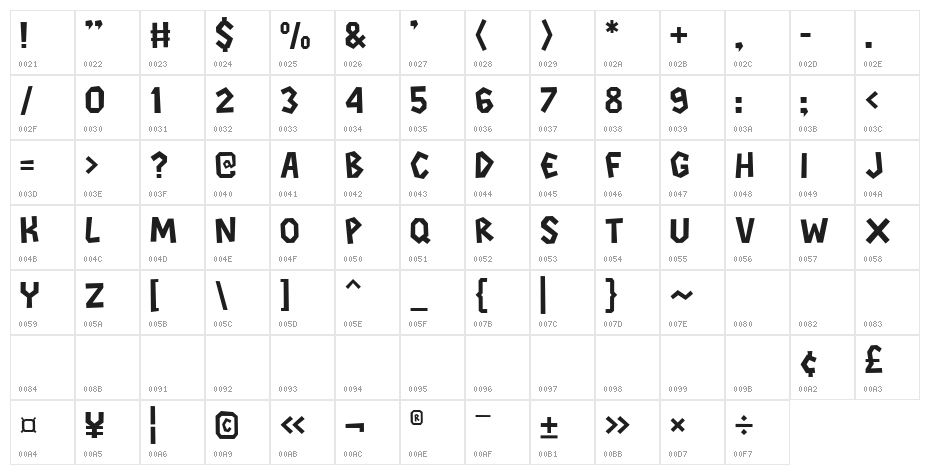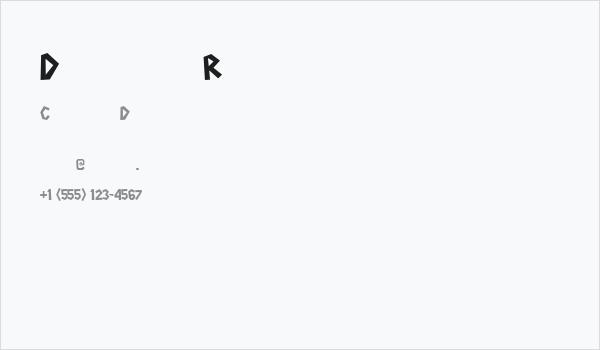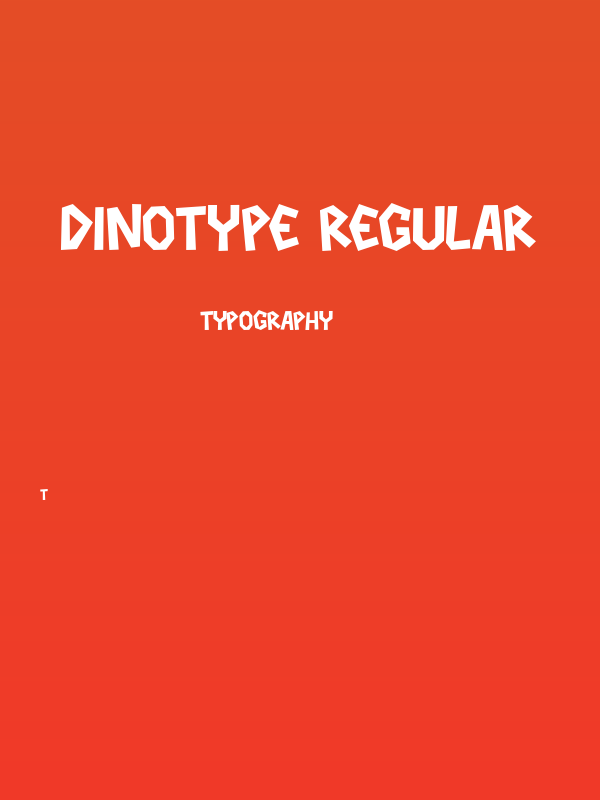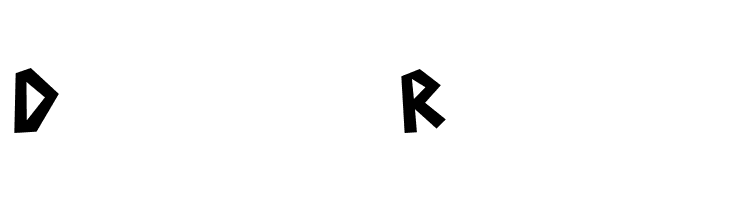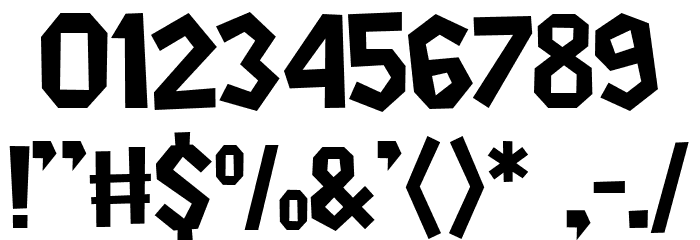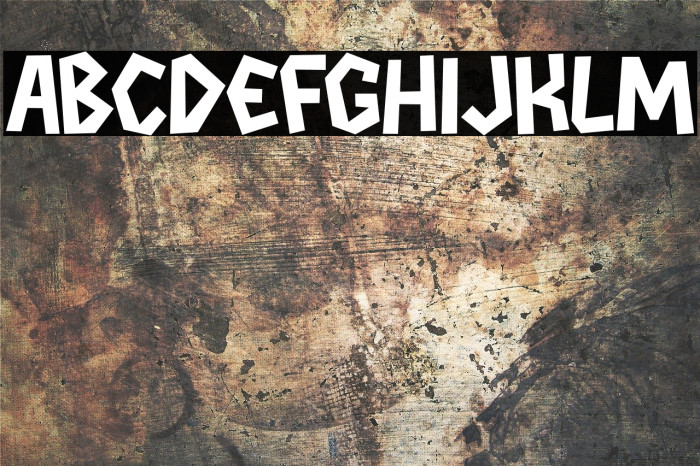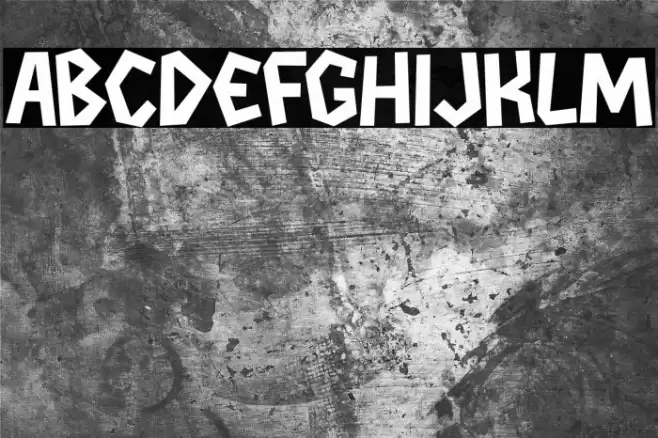
Dinotype Regular Font
✎ Cartoon
Fonts by Mahmud Fajar Rosyadi
| 名前 | Dinotype Regular |
| フォントファミリー | Dinotype |
| カテゴリ | Cartoon |
| おすすめプロジェクト | Ideal for use in posters, logos, and branding materials that require a strong, modern aesthetic. |